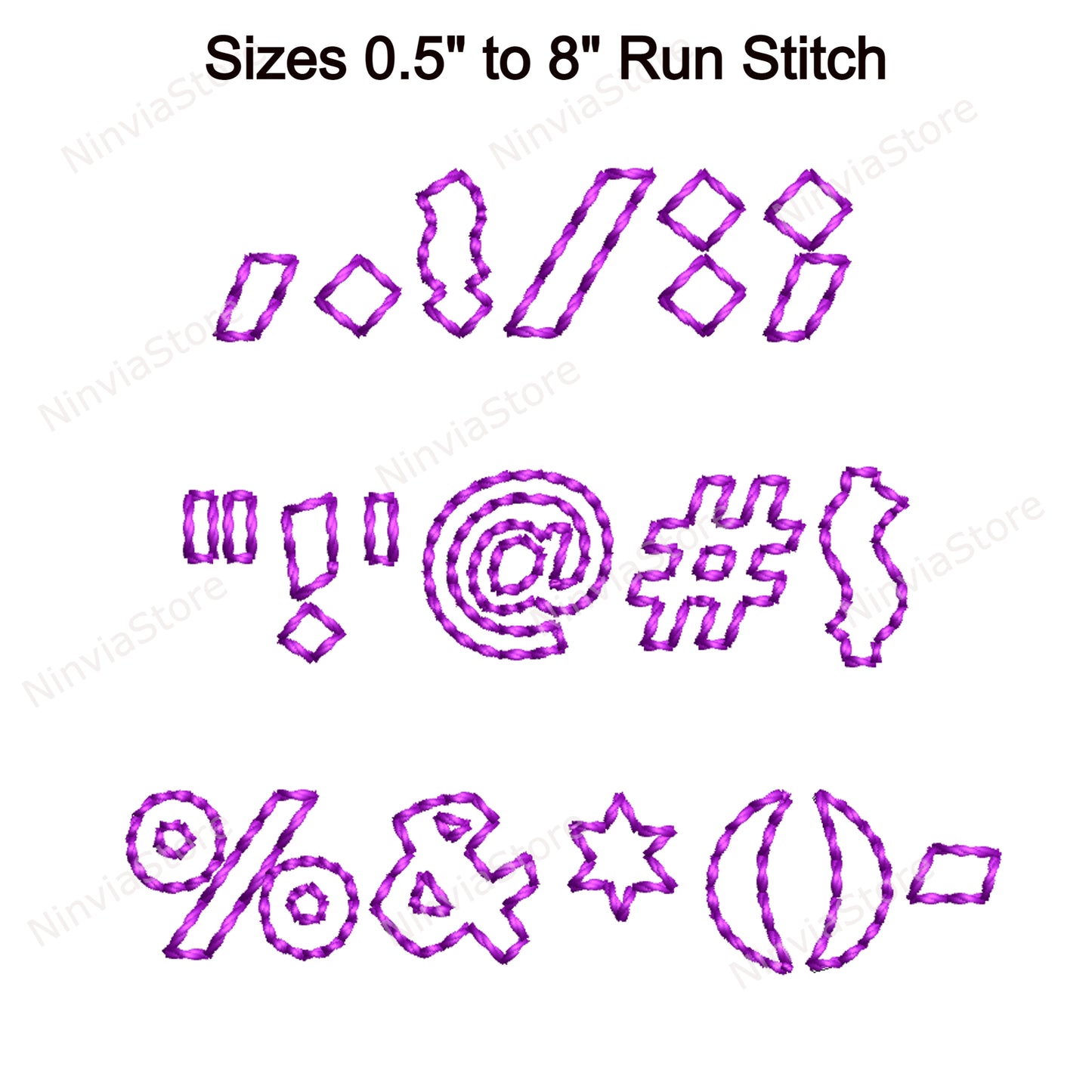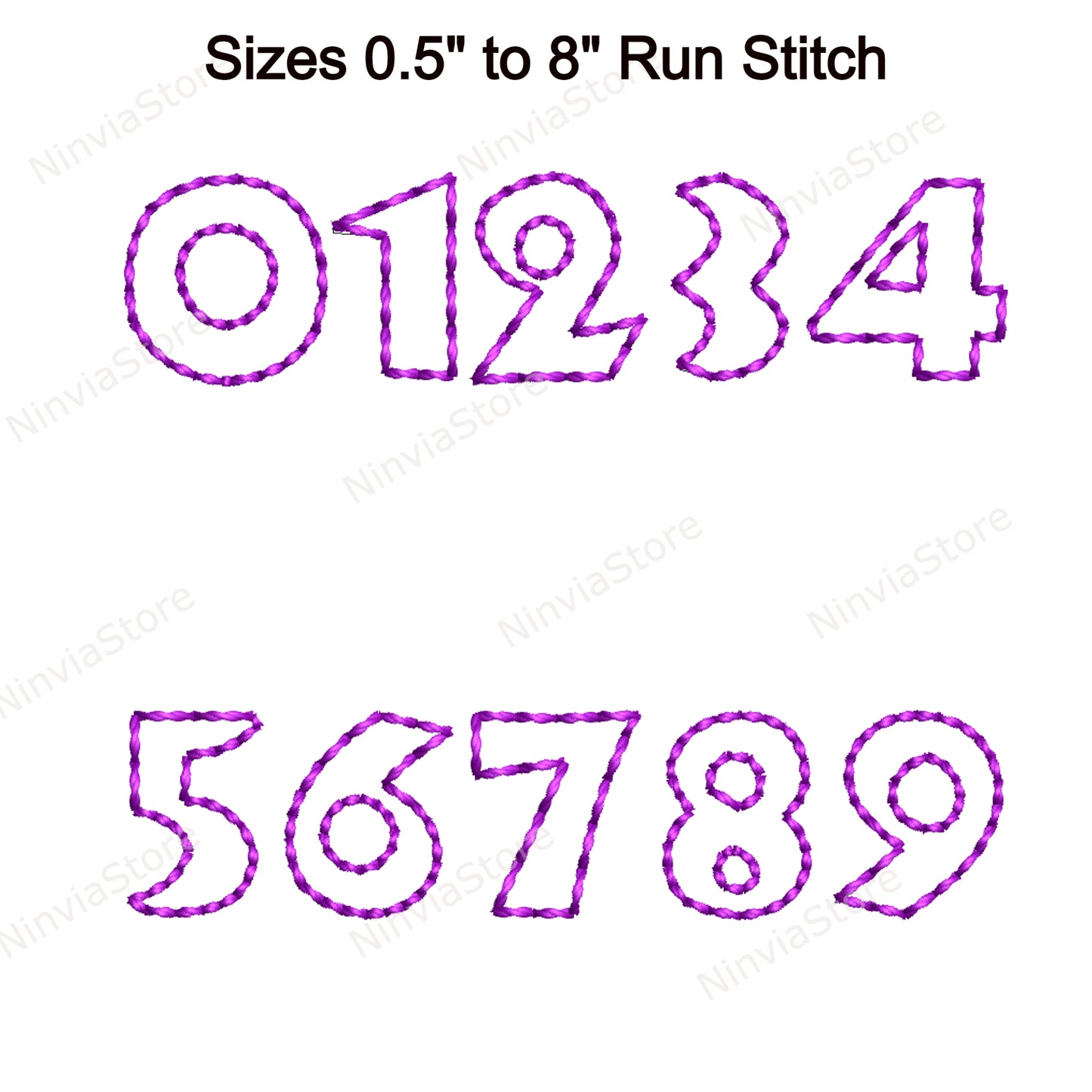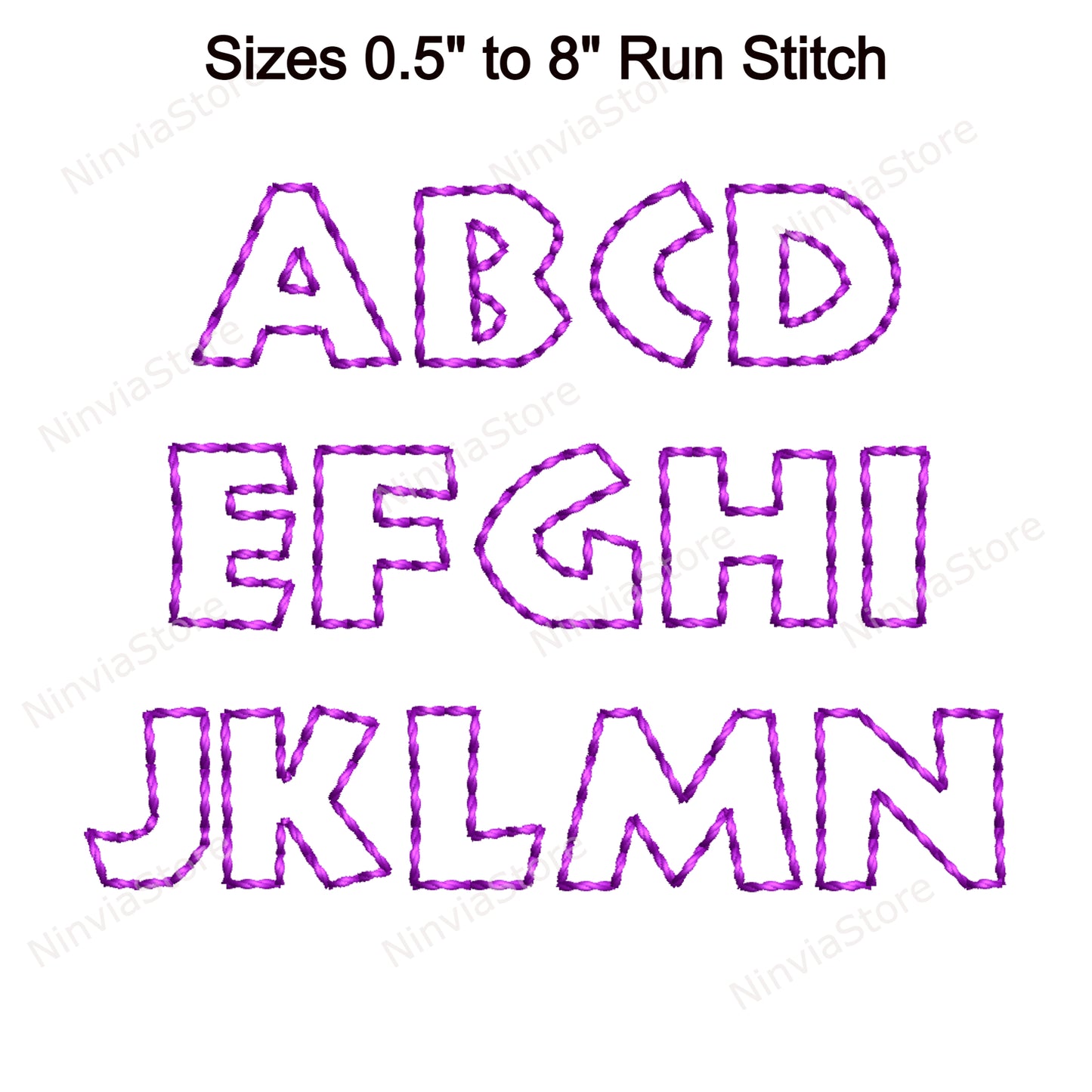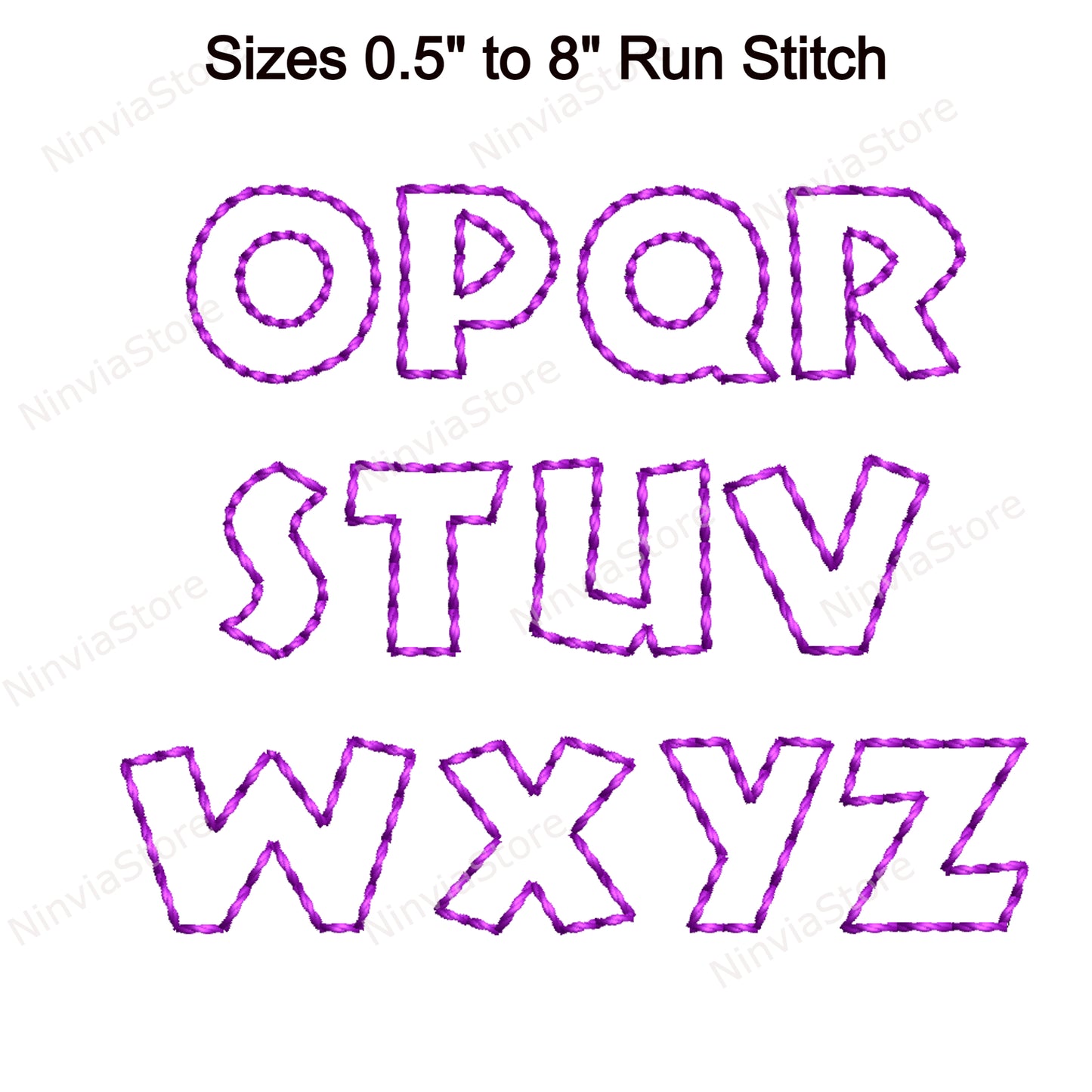
Toys Outline Bean Stitch Machine Broderie Police, 14 tailles, 8 formats, Police informelle Run Stitch BX, Police PE, Monogram Alphabet Broderie Designs
UN POINT TRIPLE PASSAGE